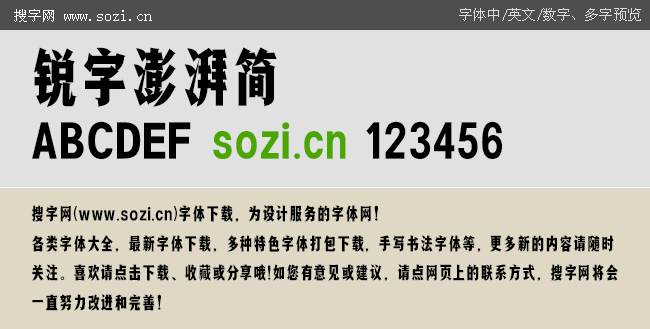
銳字澎湃簡
搜字網(wǎng)提供一款銳字澎湃簡中文字體下載,銳字澎湃簡靈感來源于民國字體,文革時期在宣傳文字中流行使用的字體,具有濃濃的懷舊感。字體筆畫粗細均勻,字形偏長,筆觸粗曠。適合應(yīng)用于廣告設(shè)計、名片設(shè)計、包裝印刷、產(chǎn)品設(shè)計等應(yīng)用。